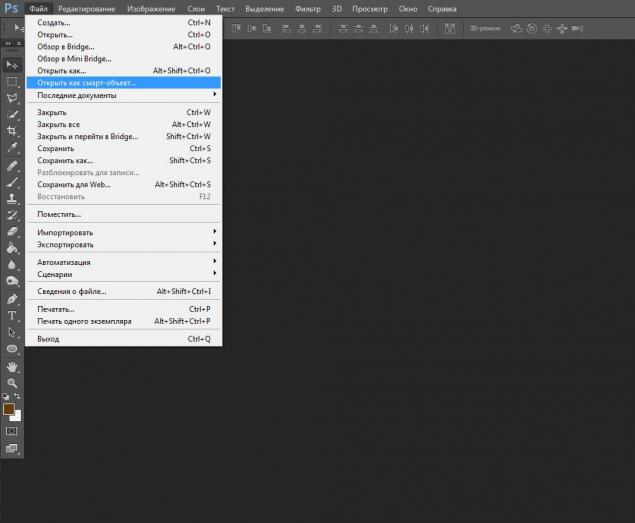
Как сделать выразительные и плотные буквы в программе фотошоп
В этой статье вы найдете подробную информацию о том, как создать эффектный толстый шрифт в Adobe Photoshop. Мы расскажем о различных методах и инструментах, которые помогут вам получить желаемый результат. Следуйте нашим рекомендациям и раскройте свою творческую сторону!
Используйте инструмент Текст в Photoshop для создания текстового элемента на вашей рабочей области.
Измените размер шрифта на более крупный, чтобы сделать его толстым и выразительным.
Примените эффект Контур или Обводка к тексту, чтобы придать ему объемность и глубину.